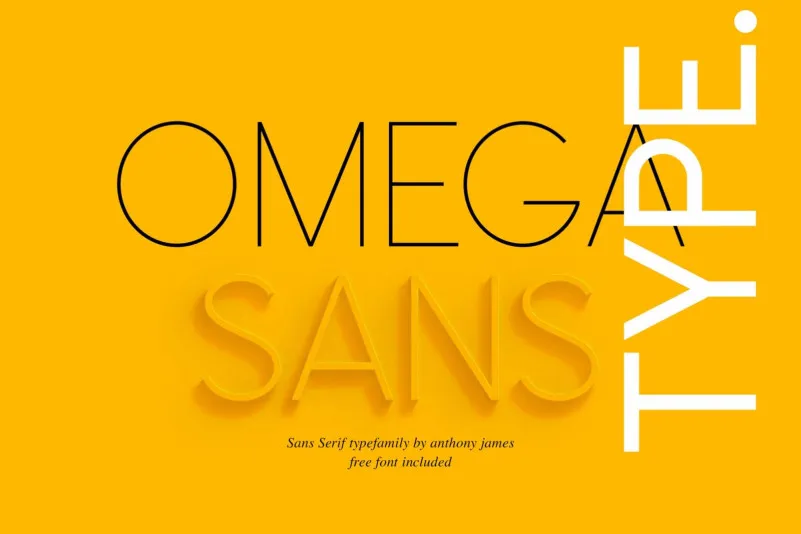
A Omega Sans Free Font é uma escolha ótima para qualquer projeto que precisa de uma impressão contemporânea e moderna. Com quatro pesos diferentes, ela oferece a versatilidade necessária tanto para logotipos quanto para headlines ou subtítulos em texto. Desenvolvida pelo designer Anthony James, esta fonte é um tipo geométrico do famoso estilo gothic sans serif que se destaca por sua personalidade única e seu brilho imediato. Esta família de fontes traz ao seu projeto um toque sofisticado sem perder a elegância e modernidade. Multilingue para 120 idiomas baseados no latim, ela é perfeita tanto para textos em inglês quanto em outros idiomas. Com sua versão gratuita, você pode experimentar as múltiplas opções de peso disponíveis enquanto mantém o design profissional e estiloso que o seu projeto merece. Através da Omega Sans Free Font, o seu próximo projeto será um marco no seu portfólio, destacando-se com uma escolha de fontes impecável.